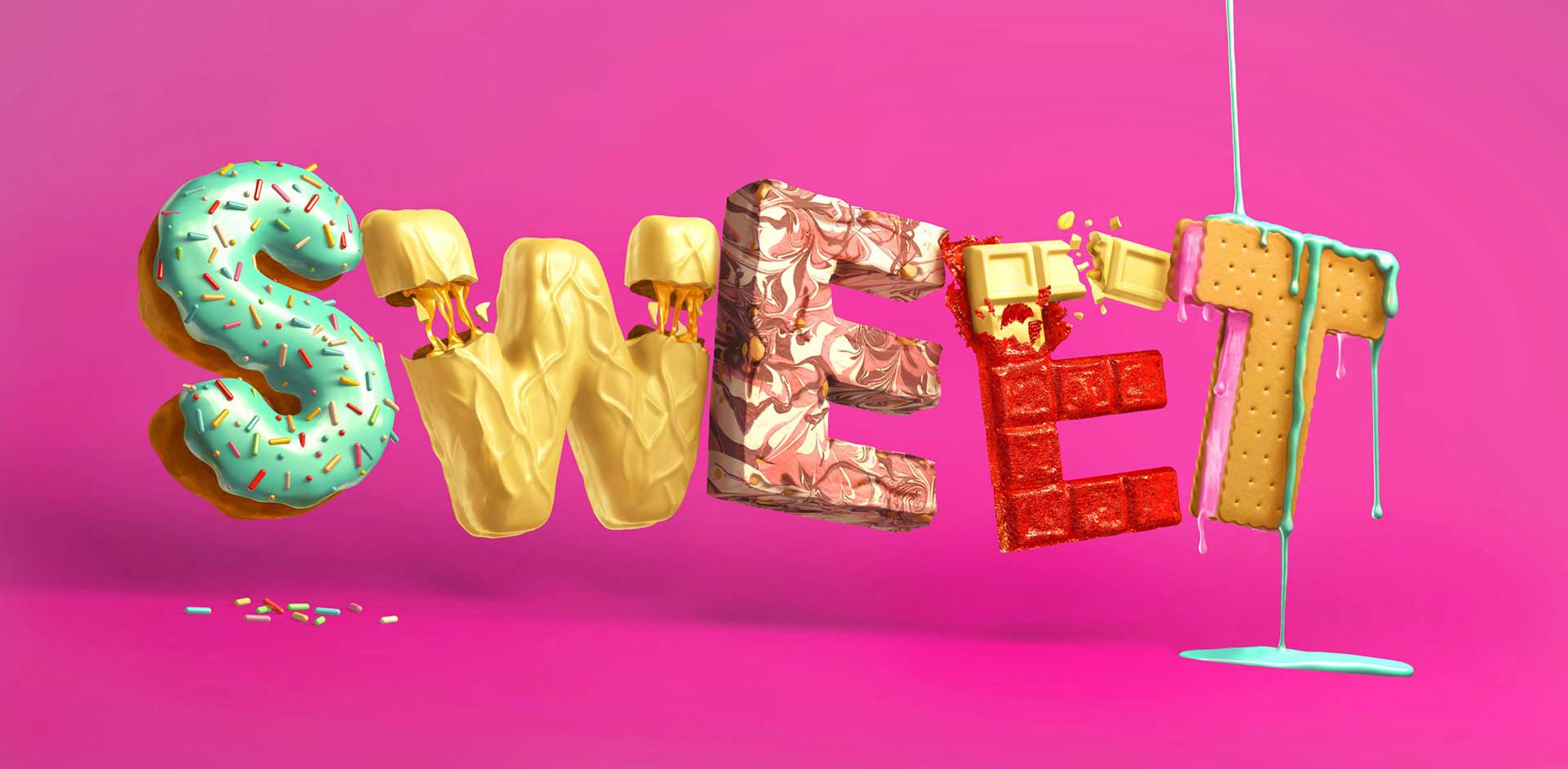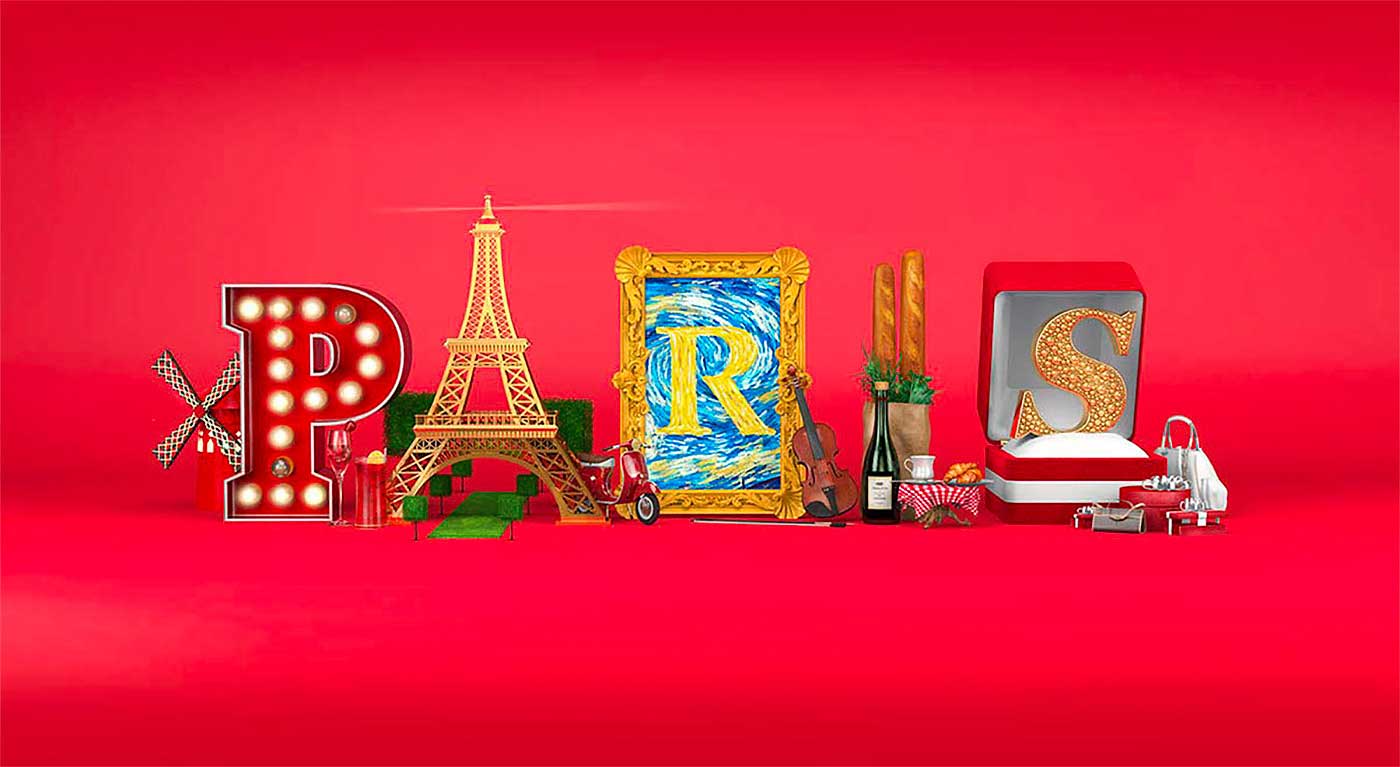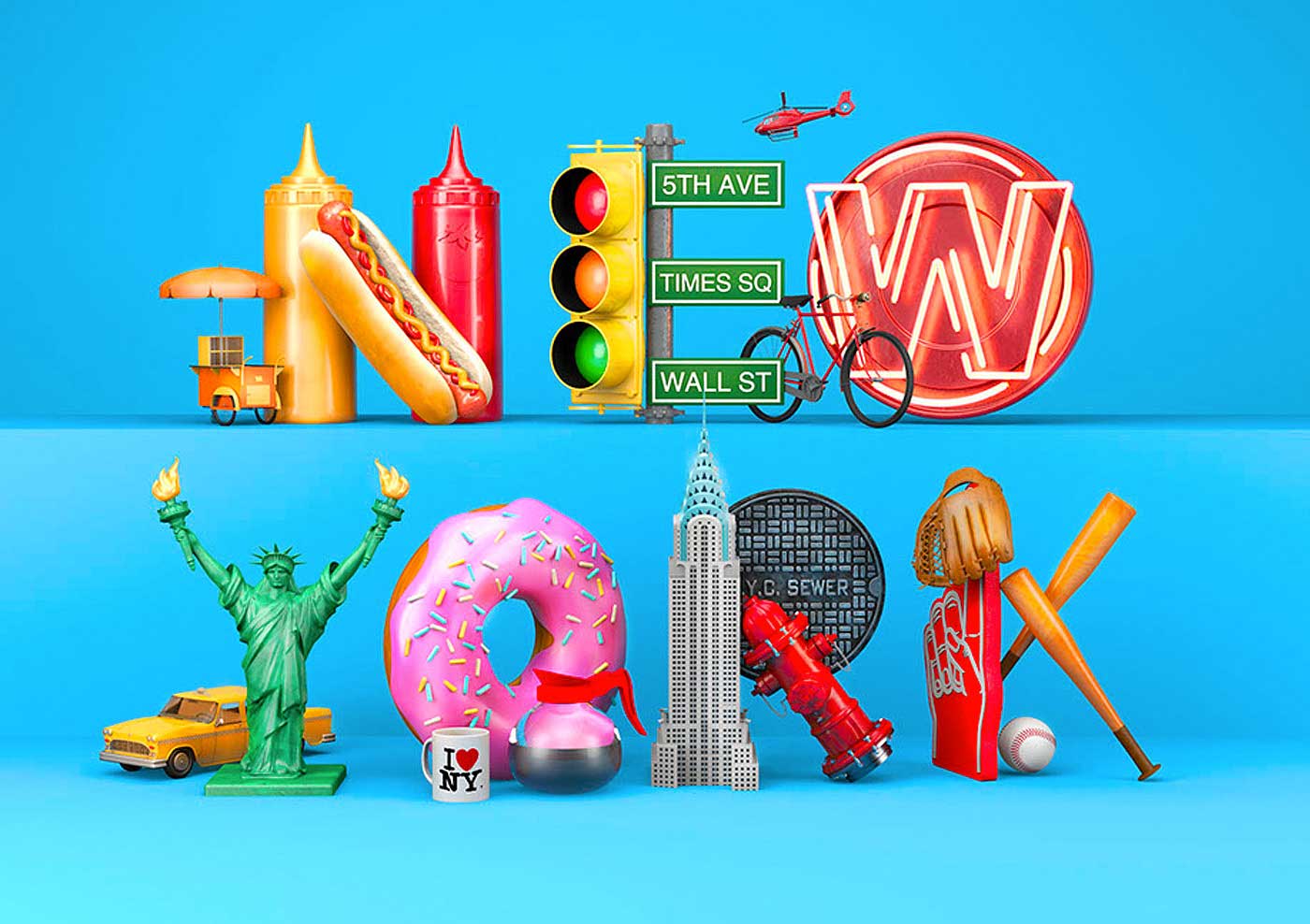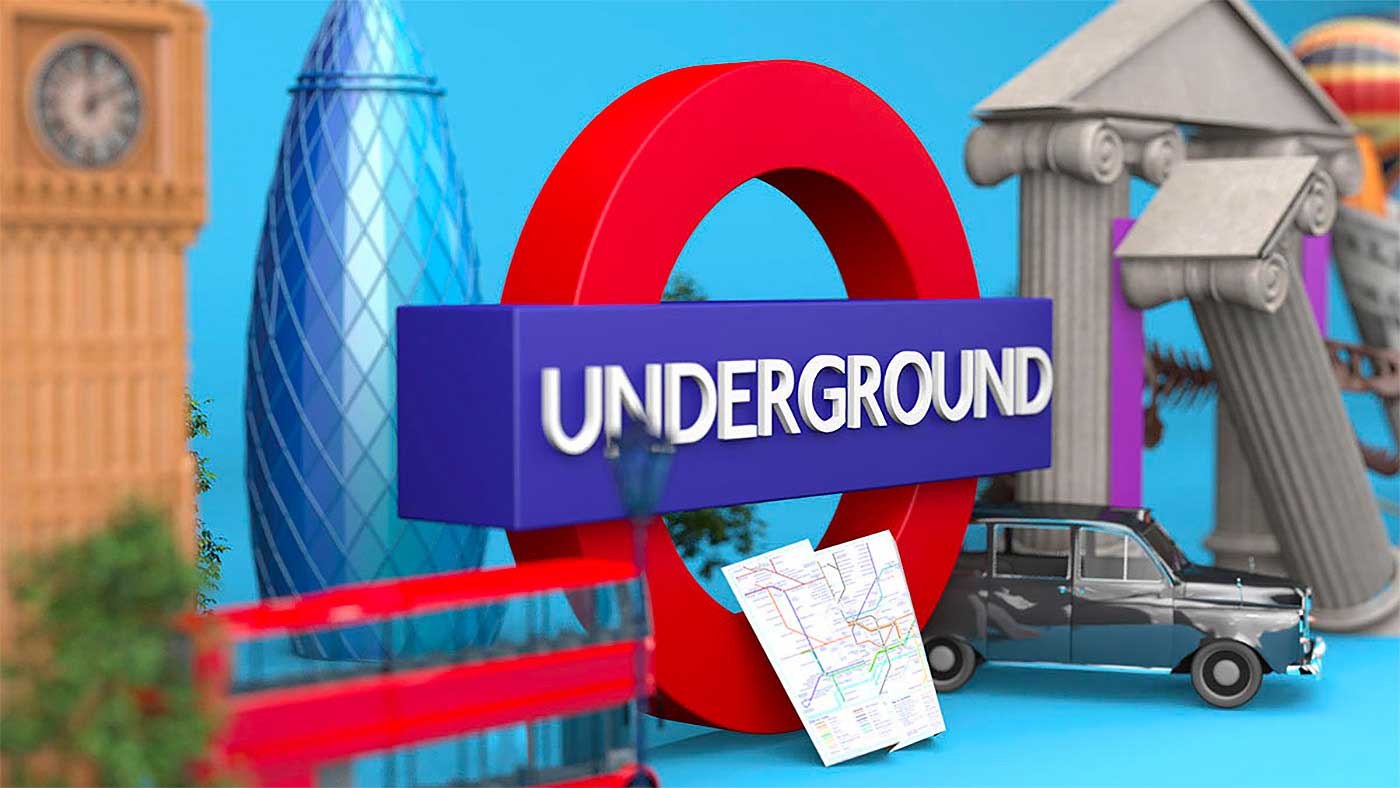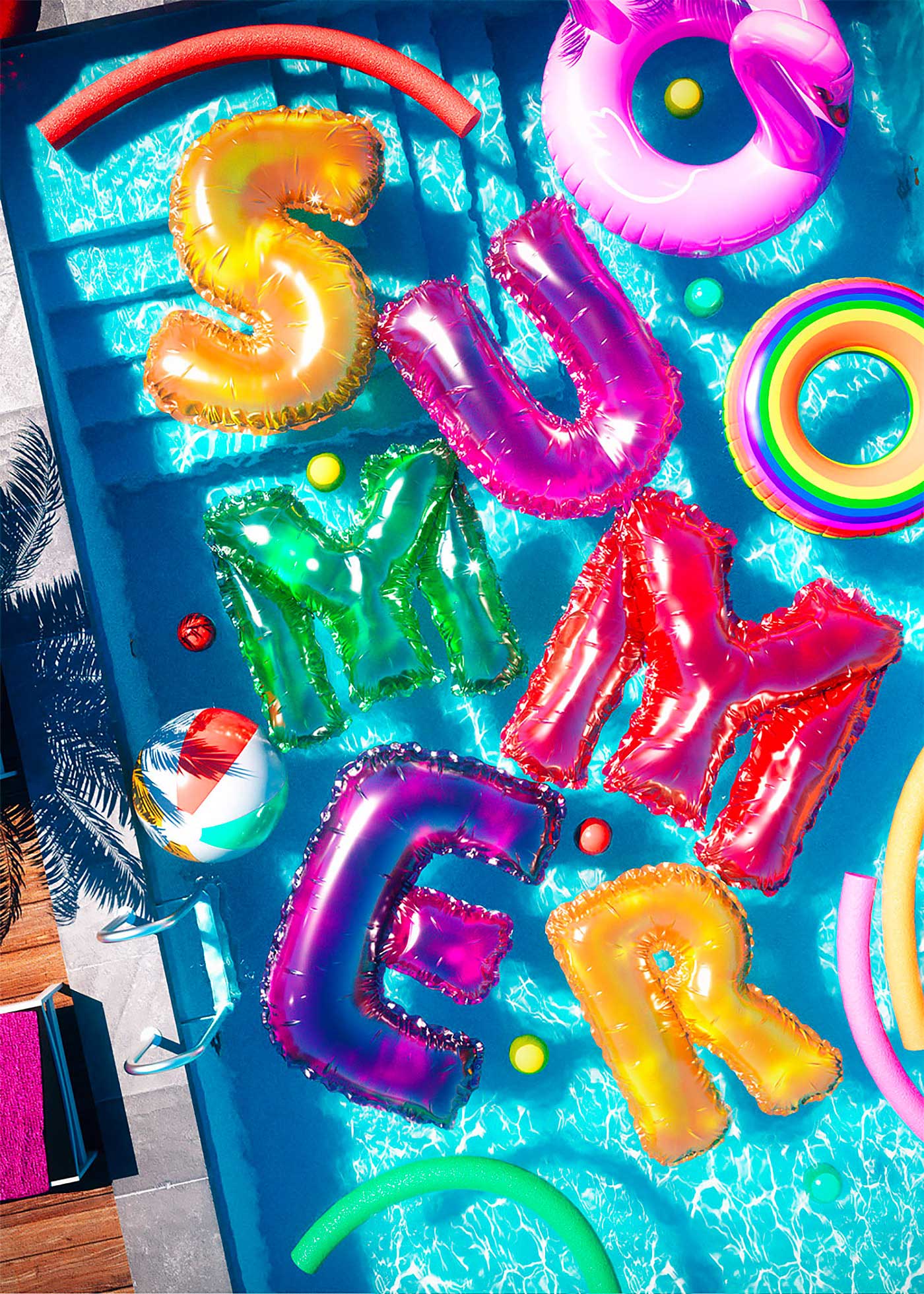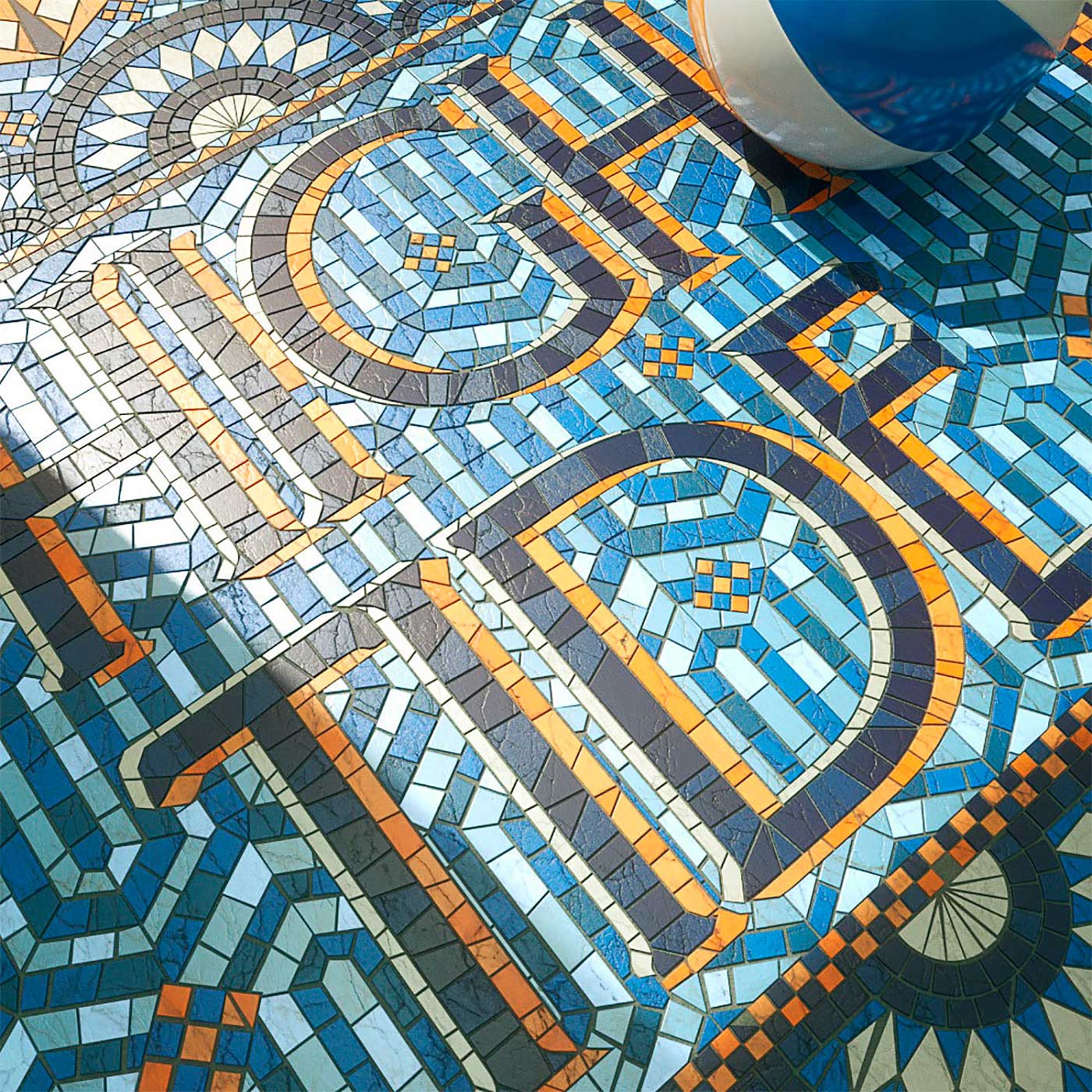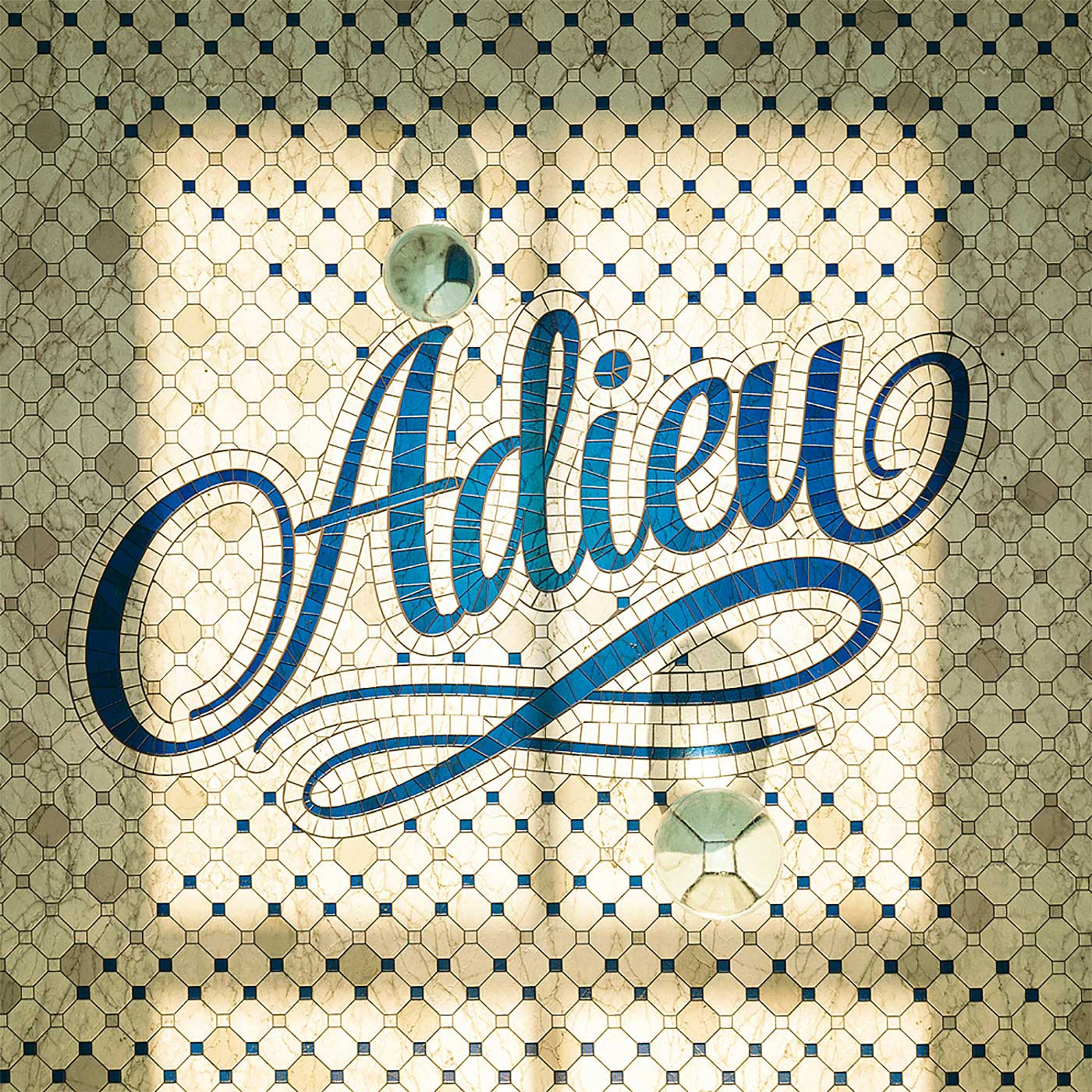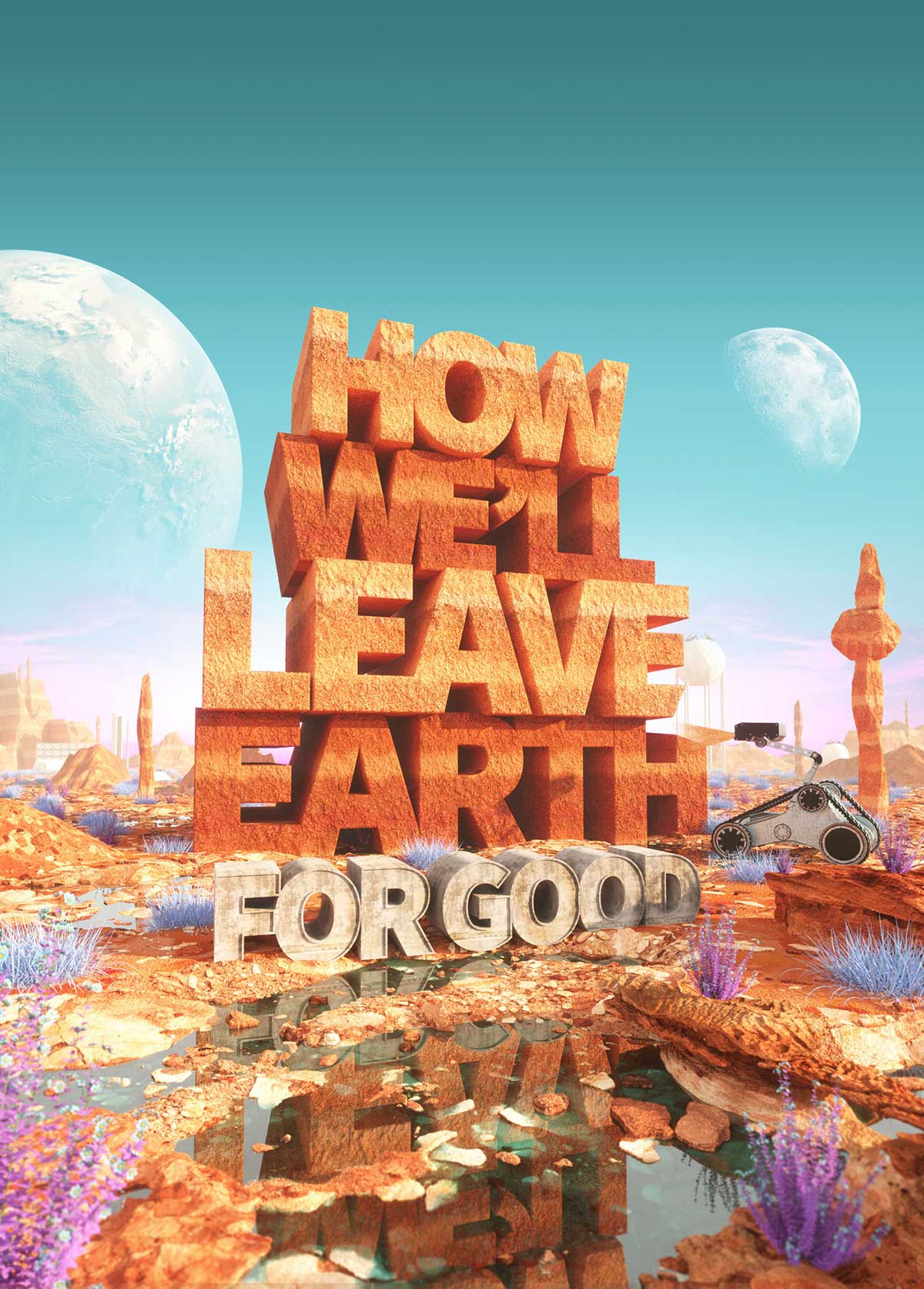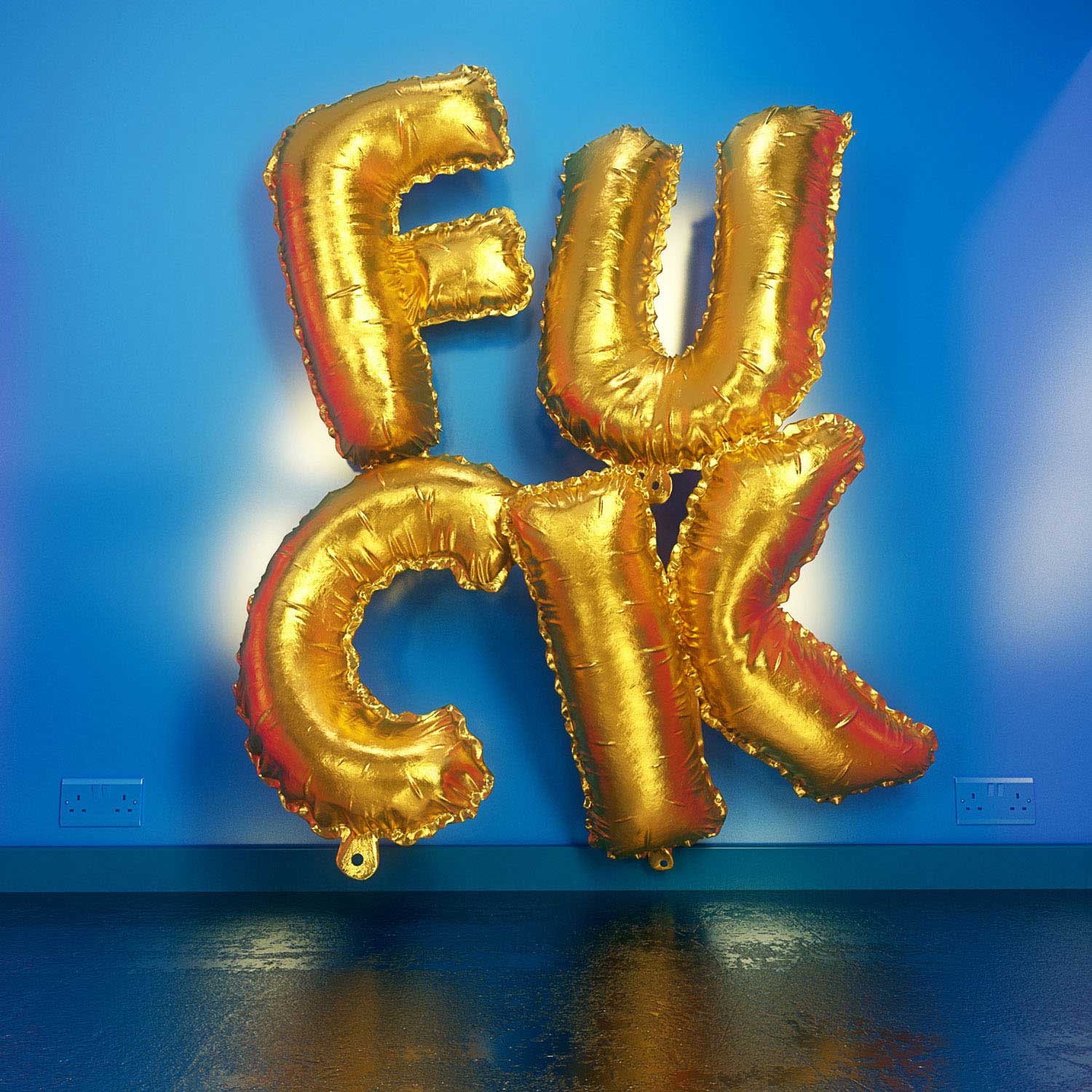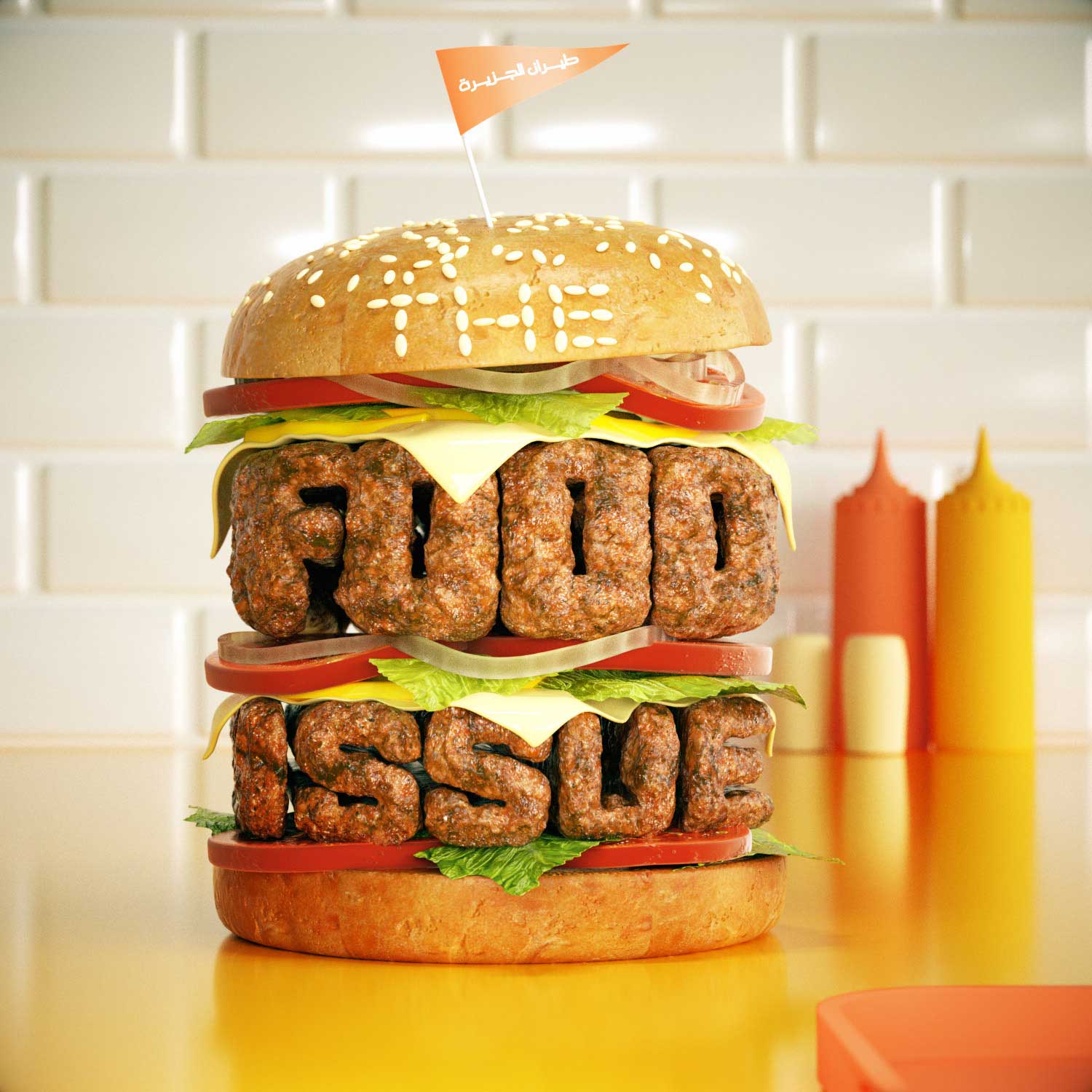
CGI und weitere Buchstaben
3D-Typografie von DUSK
Die Londoner Design-Schmiede DUSK erstellt sehr geniale 3D-Typografien am Rechner. Die schauen nicht nur durch die eine Perspektive super aus, sondern man kann wunderbar in ihnen „herumfahren“ und das Werk aus der Nähe und allerlei Blickwinkeln betrachten. Also, theoretisch, bleiben uns doch leider nur ein paar Standbilder. Wäre super, wenn man den 3D-Effekt noch mit Maus und Auge erfahren könnte. Aber auch so sind da ein paar sehr passend erarbeitete Umsetzungen dabei.
„Taking an energetic approach to design by exploring a variety of styles and disciplines, allows DUSK to deliver work that is fresh and engaging. Specialising in Typography and Illustration, whilst offering a much wider range of design services and solutions, to suit clients both big and small.“ (Agency Statement)